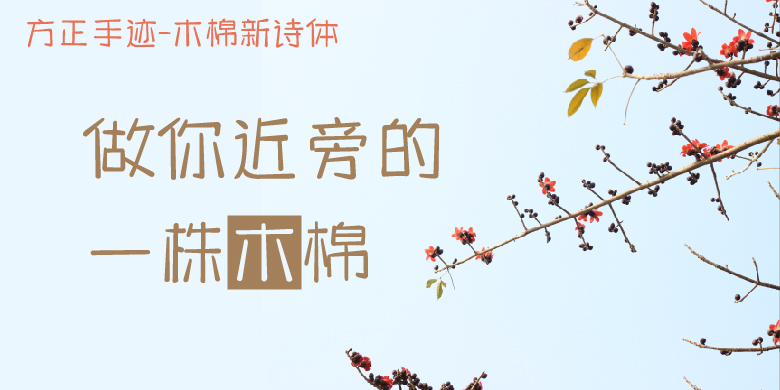
方正手迹-木棉新诗
字体品牌: 方正手迹设计师:苏新诗 字体分类:创意书写 字体属性:精品字 字符集:大陆简体(GB2312-80) 发布时间: 2018
本棉新诗用手写的方式表现规整结构,规整中带着手写的温度。像木棉的花语一样,珍惜身边的人,才是对生活最大的感恩。适用于文艺类的书刊、品牌广告和产品包装设计,以及社交网络的个性化用字。